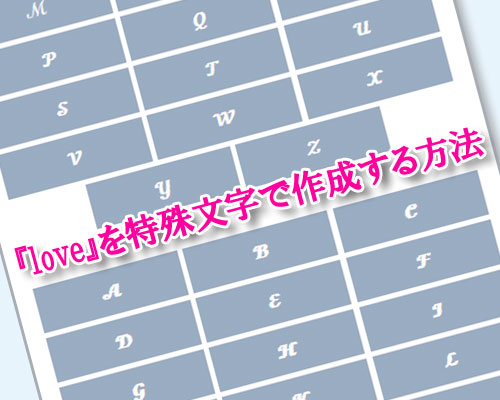
ブログ特殊文字loveフォントコピペ方法
loveを特殊文字で作成!筆記体など人気loveフォントをコピペできます
『loveを特殊文字で作りたいけど作り方がわからない。どうやったらいいの?』という質問を受けました。
特殊文字と言っても色々な種類の文字があって、スマホでは変換できない文字なども多いです。
通常は特殊文字を探してコピペするのが一般的な方法ですが、特殊文字自体を探すのは意外と面倒です。
そこで『love』フォントをコピペできるようにこのページでまとめました。
ミニフォント(小さい英字)、筆記体、斜体、明朝体、白抜き文字など、それぞれのフォントで『love』をコピペできます。
お気に入りのlove文字があればそのままコピペしてご利用下さい。
特殊文字で作成した『love』のまとめ
loveを特殊文字で作成する方法!筆記体や可愛いloveをコピペできます
よく使われている特殊文字で作成した『love』のまとめです。
大文字と小文字のアルファベットを両方掲載してるので好きなパターンを探してください。
特殊文字のミニフォント(小さい英字)で作ったlove文字
ʟᴏᴠᴇ
ˡᵒᵛᵉ
特殊文字の筆記体(花文字)で作ったlove文字
ℒ𝒪𝒱ℰ
𝓛𝓞𝓥𝓔
𝓁ℴ𝓋ℯ
𝓵𝓸𝓿𝓮
特殊文字の斜体で作ったlove文字
𝐿𝑂𝑉𝐸
𝑳𝑶𝑽𝑬
𝑙𝑜𝑣𝑒
𝒍𝒐𝒗𝒆
特殊文字の明朝体で作ったlove文字
𝙻𝙾𝚅𝙴
𝐋𝐎𝐕𝐄
𝚕𝚘𝚟𝚎
𝐥𝐨𝐯𝐞
特殊文字の白抜き文字で作ったlove文字
𝕃𝕆𝕍𝔼
𝕝𝕠𝕧𝕖
様々なloveの特殊文字を作った方法
このページで紹介した特殊文字は当サイトで提供中の特殊文字コピペツールから作る事ができます。
他にも紹介しきれなかった特殊文字が色々とあるので興味のある方はご利用下さい。
他にはないオリジナルの特殊文字を作る事もできる
少し変わった定番の特殊文字と言えば小さい英語や筆記体のようなアルファベットですが、そういう特殊文字に飽きた方は自分で作る特殊文字がオススメ。
最近では特殊文字自体を自分で作る便利ツールが人気で、多くの方がオリジナルの特殊文字を作っています。
例えば、以下のような変わった特殊文字が作れます。
loveの文字の下に『。』記号が入った特殊文字
L̥O̥V̥E̥
l̥o̥v̥e̥
loveの文字の下にニコちゃんマークのような文字が入った特殊文字
L̤̮O̤̮V̤̮E̤̮
l̤̮o̤̮v̤̮e̤̮
loveの文字を○で囲ってアンダーラインを入れた特殊文字
L⃝̲O⃝̲V⃝̲E⃝̲
l⃝̲o⃝̲v⃝̲e⃝̲
特殊文字を○で囲った特殊文字
𝕃⃝𝕆⃝𝕍⃝𝔼⃝
𝕝⃝𝕠⃝𝕧⃝𝕖⃝
このような特殊文字はloveの文字を使って色々と組み合わせて作る事ができます。
一般的によく使われている特殊文字よりも珍しい文字や可愛い文字にしたい時にはこのようなオリジナル特殊文字を作ってみるのも良いでしょう。
インスタで使える特殊文字"love"フォント活用術
インスタでおしゃれな「love」フォントを使いたいときにどのように活用すればよいのか迷っている方も多いでしょう。
特殊文字をインスタのプロフィールやブログのタイトルなどに適用する方法や文字化けしないコツをご紹介します。
これを参考にして簡単にオリジナリティあふれるデザインを作ってみてください。
インスタで特殊文字"love"を使う方法
インスタではプロフィールや投稿のキャプションに特殊文字を取り入れるとおしゃれで目を引くデザインに仕上がります。
特に筆記体や可愛いフォントの「love」を使用すると洗練された雰囲気を演出できるでしょう。
プロフィールでの使い方
インスタのプロフィール欄に特殊文字を追加するにはコピーした文字をそのまま貼り付けるだけでOKです。
ただし一部のフォントは端末によって表示されない場合があるため事前に確認するのがよいでしょう。
ストーリーズやハイライトに使う方法
ストーリーズではテキスト入力時に特殊文字を挿入できます。
おしゃれな「love」フォントを追加することで個性を際立たせることができます。
ハイライト名に取り入れるとカテゴリごとにおしゃれな印象を持たせることができます。
注意点
一部のデバイスでは特殊文字が正しく表示されないことがあります。
特にAndroidとiPhoneではフォントの互換性が異なるため閲覧環境を考慮して使用するのがよいでしょう。
LOVEの種類を使い分けるポイント
LOVEの特殊文字は大文字・小文字・ハート付き・囲み文字・斜体・装飾付きなどさまざまなタイプが存在します。
たとえば「🅛🅞🅥🅔」のような囲み文字はポップな印象を与え「𝓛𝓸𝓿𝓮」のような筆記体はやわらかくエレガントな雰囲気を演出します。
かわいい雰囲気を出したい時は「ʟᴏᴠᴇ」など小文字ベースのフォントもおすすめです。
気分や投稿のトーンに合わせて文字の雰囲気を変えてみましょう。
インスタでの使用シーン別活用法